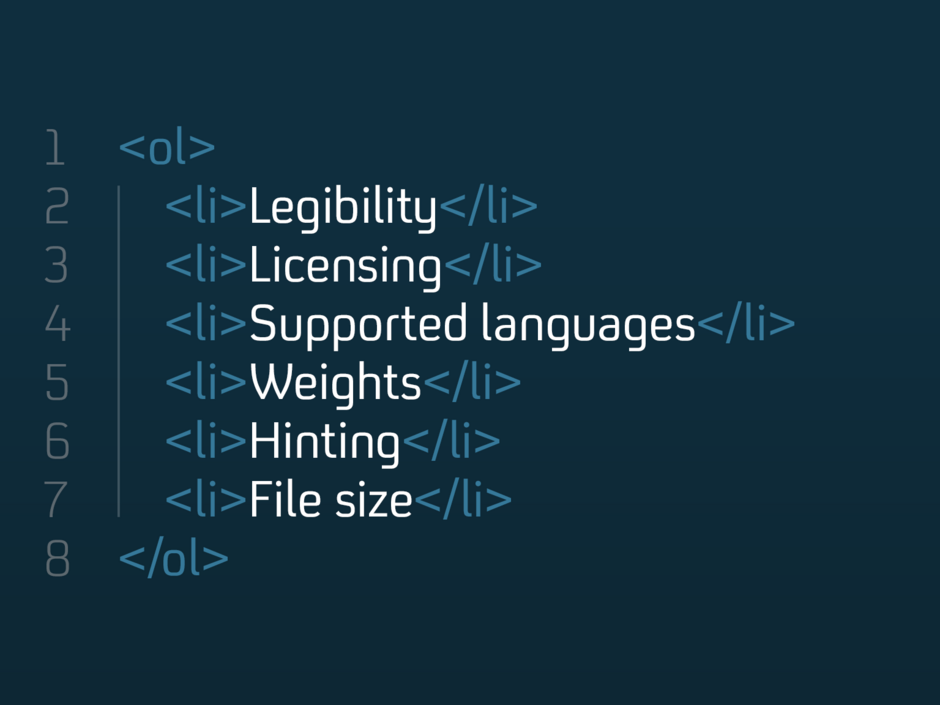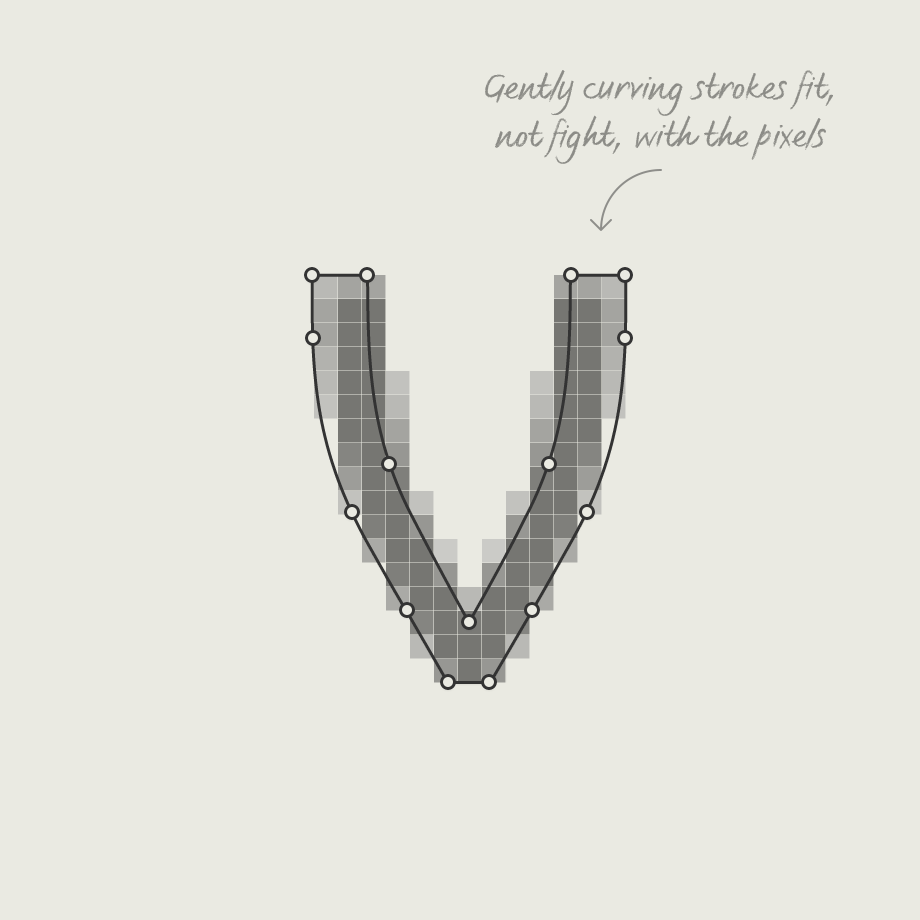
¿Qué es lo que realmente importa con las fuentes web?
Hemos avanzado mucho desde los tiempos de las fuentes seguras para la web y ahora hay una enorme variedad de tipos de letra entre los que elegir. La diferencia entre lo que vemos en línea y lo que vemos impreso sigue siendo enorme, pero ¿se está acortando la distancia a medida que avanza la tecnología? Según el archivo HTTPJason Smith
/embedded webfonts, pero sigue habiendo muchas ideas equivocadas sobre lo que funciona en Internet. Las cosas se mueven con rapidez y las normas cambian constantemente. Si a esto le sumamos los consejos confusos y a menudo contradictorios de diversas publicaciones y blogs, puede resultar difícil saber cuáles son las mejores prácticas actuales.El resultado es que las marcas optan por lo que consideran una elección segura y pierden una gran oportunidad de diferenciarse de sus competidores, cuando el tipo de letra es a menudo el único activo visible de la marca. Algunos de los tipos de letra más utilizados, como Arial y Helvetica, no son los más legibles y los costes de licencia de los tipos de letra omnipresentes en los sitios web pueden ser asombrosamente altos. Se pone demasiado énfasis en diseñar fuentes para pantallas muy pequeñas hacia arriba. El diseño de marca y UX debería exponer la arquitectura de la marca a través de todos los puntos de contacto y, si se diseñan correctamente, las fuentes de la marca deberían traducirse tanto hacia abajo como hacia arriba. La interfaz, el diseño de UX y la tipografía no consisten en conseguir que la fuente sea lo más pequeña y clara posible. Se trata de que la información sea lo más clara posible. El tamaño es tan importante en Internet como en la impresión, así que hay que ser sensato con los tamaños .px y .pt.El 60% de los sitios web utilizan fuentes personalizadas
Está muy extendida la idea de que las fuentes sans serif limpias son la elección segura para múltiples tamaños de pantalla, pero lo cierto es que las fuentes serif bien elaboradas también pueden funcionar y facilitar la lectura de textos largos. Para añadir un poco más de confusión, todas las fundiciones ofrecen fuentes web, pero algunas se especializan en versiones específicas para la web, mientras que otras diseñan específicamente para la web.
¿Cuáles son las consideraciones más importantes? He aquí mis principales consejos:
1. La legibilidad es y será siempre importante. Los principales aspectos a tener en cuenta son una gran altura x, poca ambigüedad entre caracteres y contadores y terminales abiertos. Esto también es importante para los materiales impresos fuera de línea, pero en línea hay más variables a tener en cuenta, como el tamaño de las pantallas y los efectos de las pantallas retroiluminadas. Merece la pena plantearse quién es su público, qué dispositivos utiliza y cómo hacer que su contenido sea lo más accesible posible. Si desea más información, consulte este artículo en
3. Compruebe qué idiomas son compatibles. Aunque sólo opere en un país, ¿tiene planes de expandirse a otros y podría esto causar problemas si, por ejemplo, el ruso no es compatible pero es un área potencial de crecimiento? La correspondencia tipográfica (cuando se encuentra una alternativa similar) suele ser suficiente para alfabetos con una estructura muy diferente a la latina, como el chino o el árabe, y puede resultar más rentable.
4. Los pesos son muy importantes. En la web tiene que haber una gran diferencia entre Regular y Negrita. El color y el antialiasing afectan al soplado de píxeles y al relleno. También hay que probar los fondos positivos y negativos, ya que pueden hacer que los pesos parezcan muy diferentes. Tipos de letra como
oFS Millbank, que cuentan con un gran número de variaciones de peso, pueden ayudar a resolver estos problemas y garantizar un mejor resultado global.5. Hay dos opciones principales de alojamiento a considerar: Autoalojamiento o alojamiento a través de un tercero como Adobe TypeKit. Con esta última opción no recibes los archivos de fuentes, sino un pequeño fragmento de código para colocar en tu sitio web. La principal ventaja de esta opción es que puede ser considerablemente más barata para sitios pequeños y que se tiene acceso a muchos tipos de letra de diferentes fundiciones. La ventaja del autoalojamiento es que usted mismo obtiene la licencia de los archivos de fuentes, lo que significa que no tiene que depender de un servicio de terceros para que sus fuentes sigan funcionando.FS Sin título
6. Insinuación: A pesar de las mejoras en la resolución de las pantallas, la sugerencia de fuentes sigue siendo un proceso esencial. Una vez diseñado el tipo de letra, se ajusta para que sea lo más legible posible en la pantalla del ordenador, teniendo en cuenta cómo se representan las formas cuando se convierten en grupos de píxeles. Esto solía llevar mucho tiempo, pero ahora el ajuste manual es mucho más sencillo y no debería costar un ojo de la cara. La mayoría de las fundiciones automatizan el proceso de hinting y disponen de algunos trucos inteligentes para conseguir un resultado muy decente. Algunos tipos de letra se diseñan para que se adapten a los píxeles desde el principio, lo que reduce aún más la dependencia del hinting.
7. Tamaño del archivo de la fuente. A diferencia de las imágenes, el tamaño de los archivos de los tipos de letra suele ser relativamente pequeño, pero los tiempos de carga son importantes, por lo que conviene mantenerlos al mínimo. Asegúrese de adquirir una licencia de fuente web auténtica, ya que los archivos habrán sido optimizados adecuadamente por el diseñador tipográfico para lograr la máxima eficacia. Convertir los archivos de escritorio en WOFF o EOT mediante software de terceros puede aumentar el tamaño del archivo (además de suponer un incumplimiento masivo de los términos de la licencia).
En general, a medida que las pantallas y la tecnología mejoren a pasos agigantados, las opciones tipográficas se ampliarán y las marcas digitales empezarán a distinguirse cada vez más unas de otras.